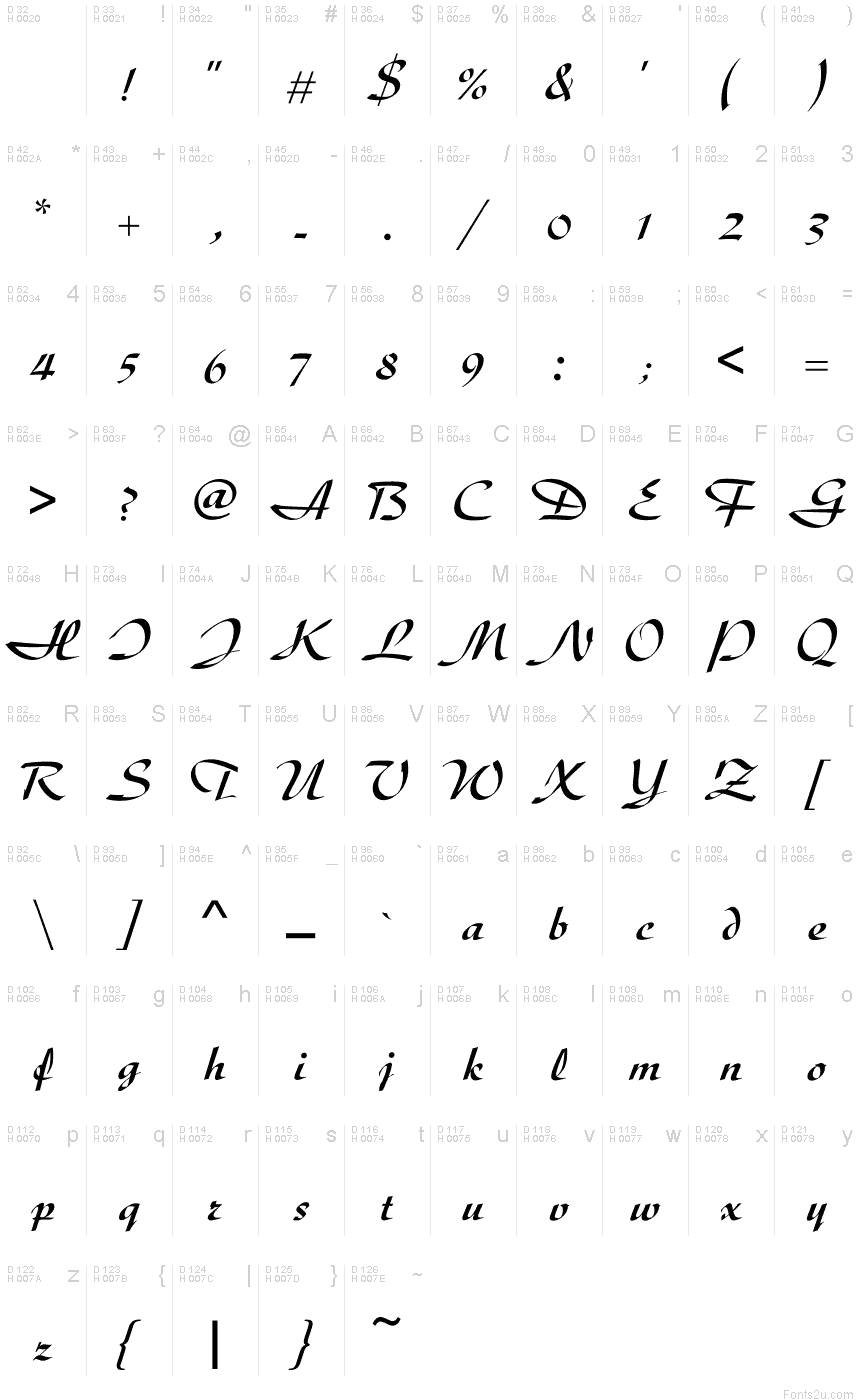
UKIJ Diwani von der Uyghur Computer Science Association ist eine kostenlose Diwani-Schrift mit dem fließenden, höfischen Rhythmus osmanischer Manuskripte. Die Buchstaben bestechen durch lange, spitz zulaufende Striche, tiefe Schwünge und scharfe, hakenförmige Abschlüsse, wodurch das Gesamtbild eher zeremoniell und flüssig als bloß ornamental wirkt.
Es eignet sich hervorragend für Kulturplakate, Buchtitel, Einladungen, Titelschilder und kurze Branding-Elemente, bei denen nur wenige Buchstaben ausreichen müssen, um die Stimmung zu tragen. Als kostenlose Schrift funktioniert sie am besten für kurze Überschriften und Monogramme, da die schwungvollen Kurven und verlängerten Endungen selbst kurzen Wörtern das Flair formeller Kalligrafie verleihen.